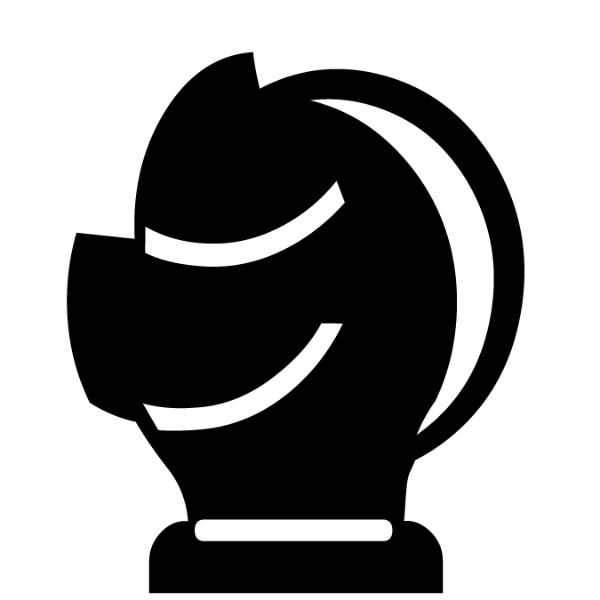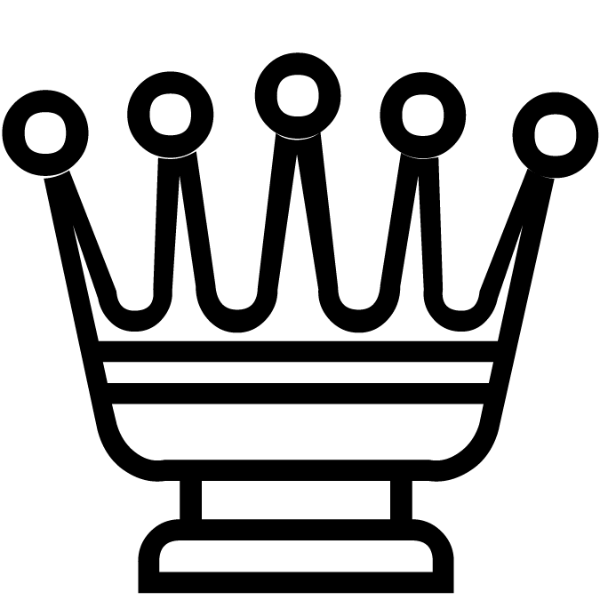
La Fuente Chess Medieval es una creación única que se inspira en la estética y la simbología del medioevo, con un diseño estilizado y artístico. Destacan especialmente el Alfil y el refinamiento gráfico de todas las piezas, evocando la atmósfera de una época histórica llena de simbolismo.
Juego de Ajedrez con la Fuente Medieval: